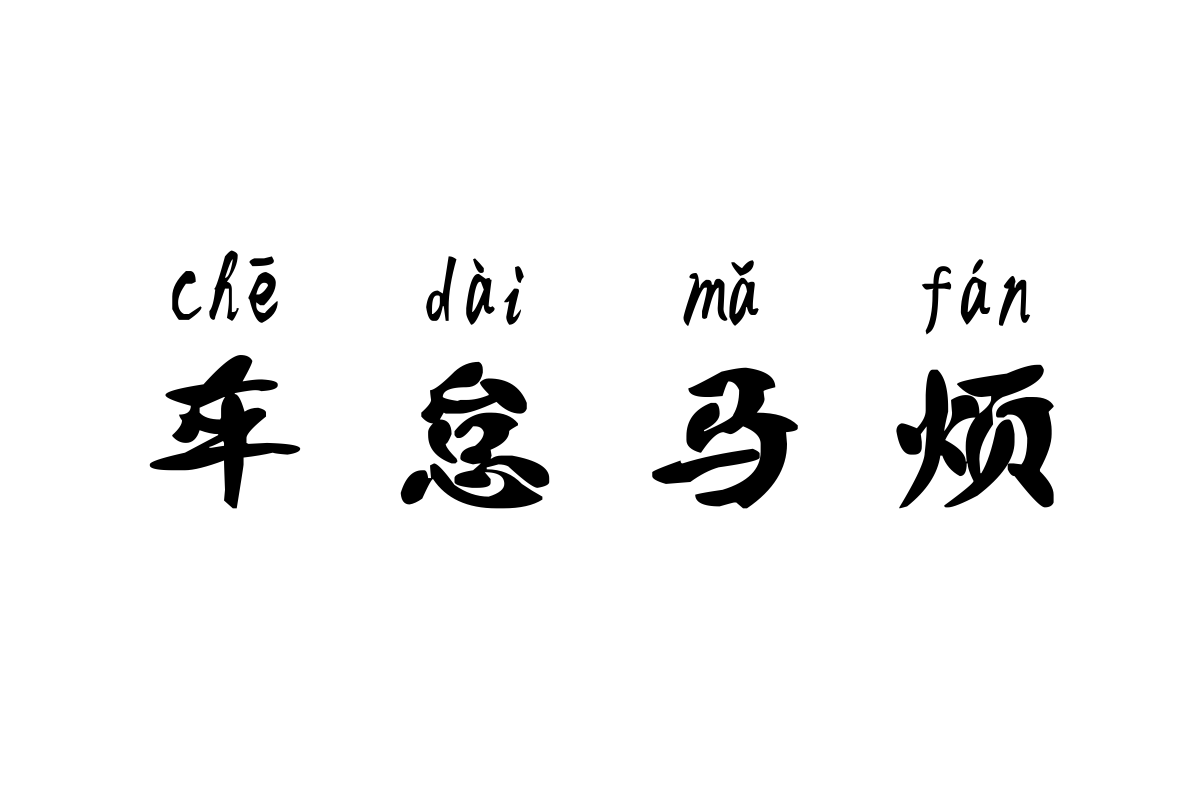
汉标粗犷拼音字体是一种具有强烈视觉冲击力的中文字体。它采用了大胆、粗犷的设计风格,通过夸张的笔画和结构,传达出一种强烈的个性和力量感。这种字体适用于需要强调品牌个性、传递强烈情感或表达独特创意的场合。
汉标粗犷拼音字体的特点在于其独特的笔画结构和形状。它的笔画粗壮有力,线条流畅而有力,给人一种强烈的视觉冲击。同时,这种字体还注重整体的协调性和美感,通过巧妙的排列和组合,使整个字体看起来既简洁又富有层次感。
此外,汉标粗犷拼音字体还具有一定的可读性。虽然它采用了夸张的设计手法,但仍然保持了一定的清晰度和易读性,使得读者能够在欣赏美感的同时,也能感受到文字的清晰和准确。
总的来说,汉标粗犷拼音字体是一种极具个性和力量感的中文字体,适合用于需要强调品牌个性、传递强烈情感或表达独特创意的场合。